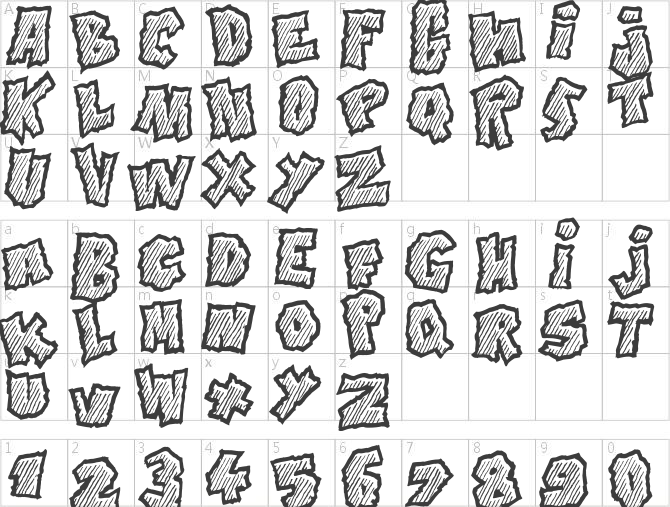
Doonga Slash
Doonga Slash介紹
Doonga Slash字體字庫是一款讓人賞心悅目、百看不厭的英文字體,適合各類廣告和產(chǎn)品包裝設(shè)計應(yīng)用,字體大小0.12MB,格式為ttf字體,上傳用戶是澤澤,作者/版權(quán)方為未知
Doonga Slash效果圖